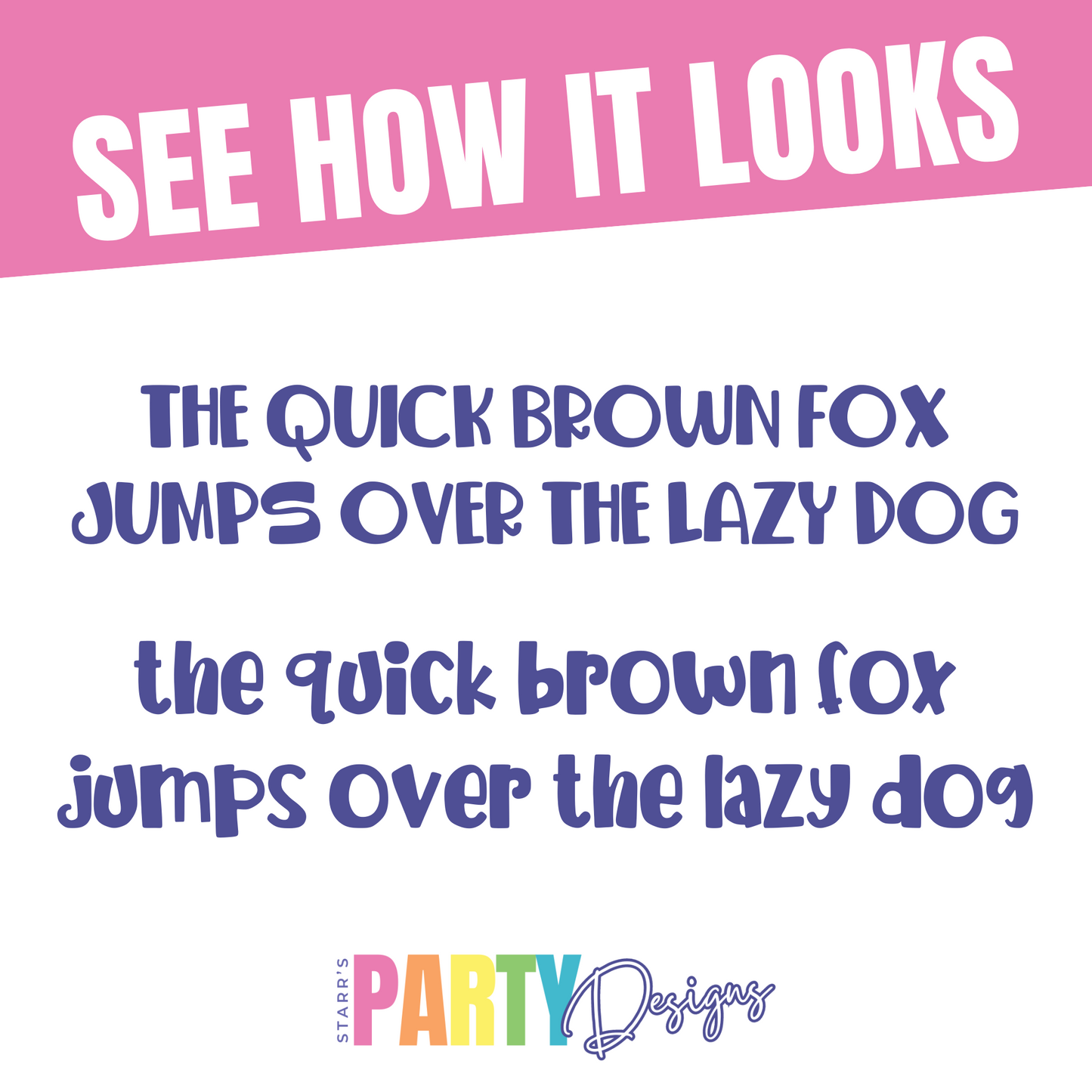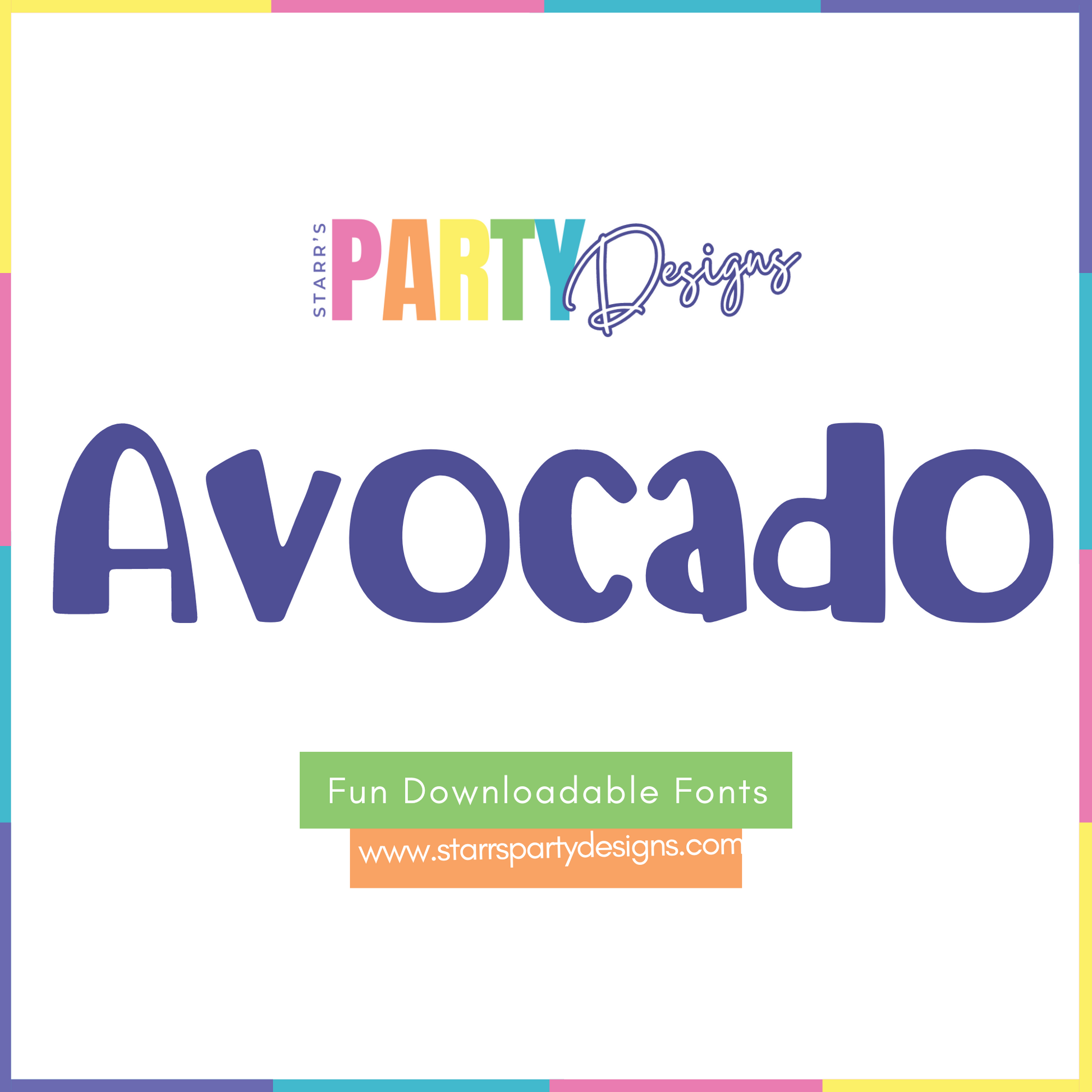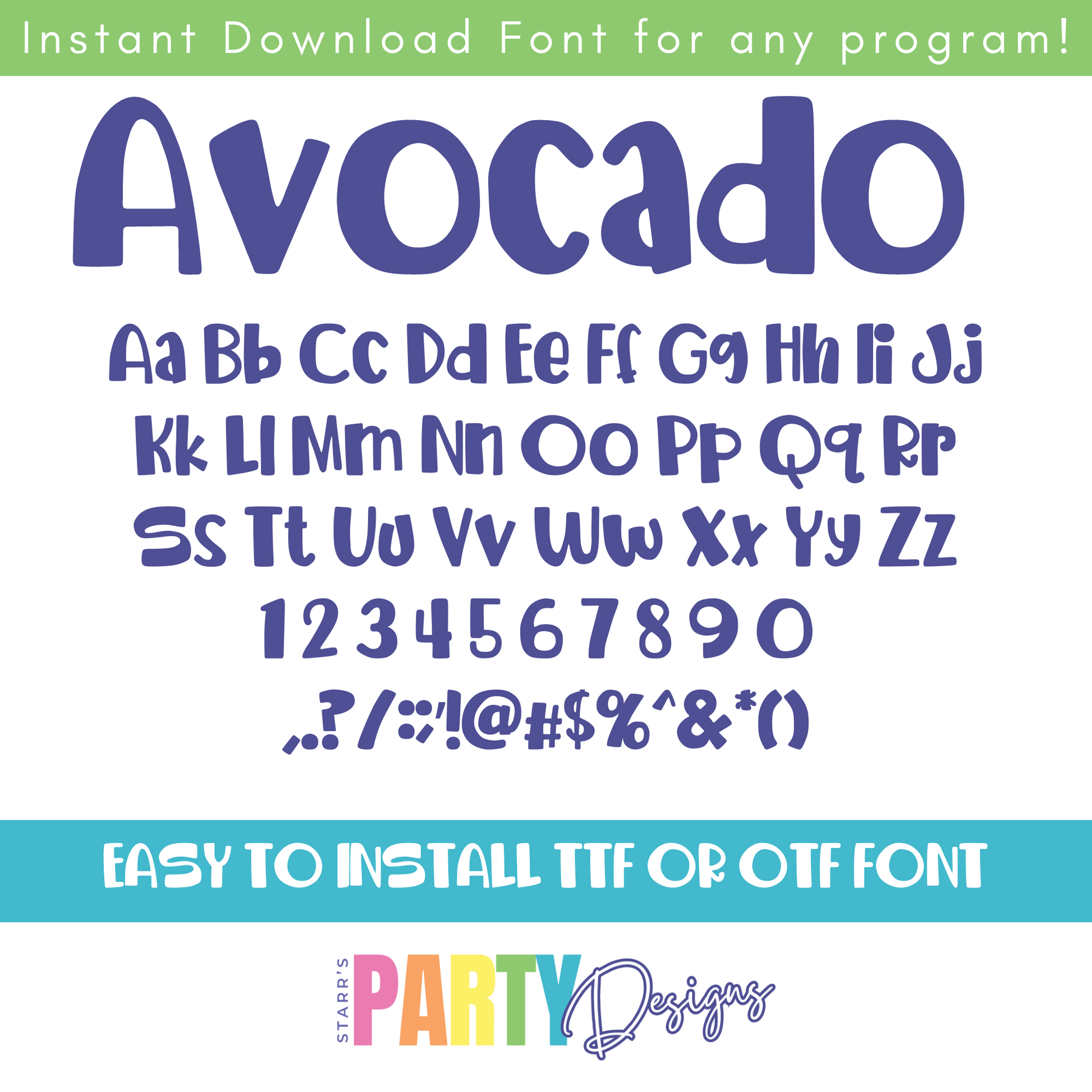
FUENTE DE AGUACATE
¡AVOCADO es perfecto para: manualidades de diseñadores, logotipos, marcas, archivos svg, tarjetas de felicitación, procreate, camisetas, carteles, redes sociales, impresiones de agendas y más!